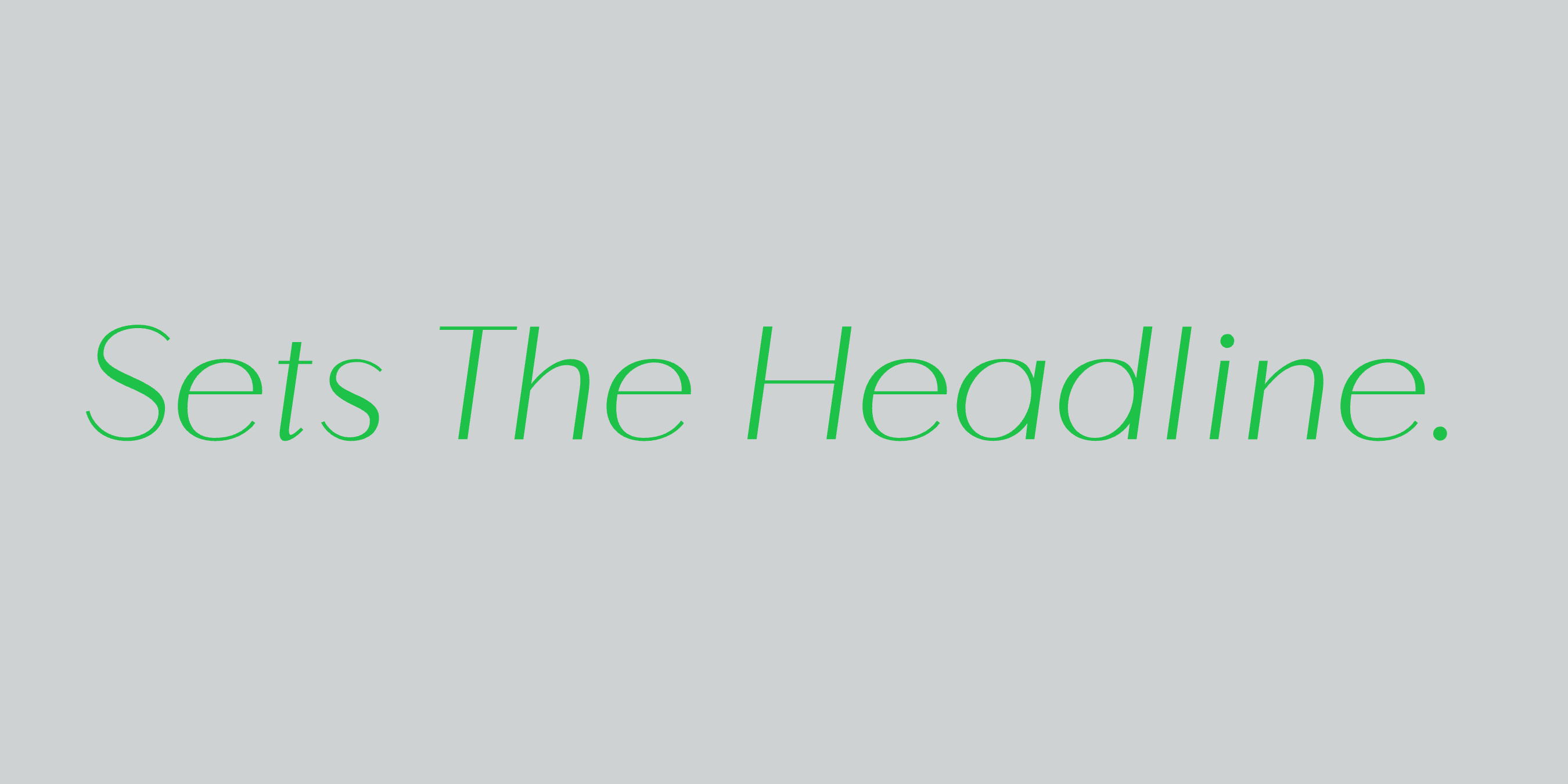
Moderne Display-Schriften für Editorial Design und Branding
Display-Schriften sind Typografie in ihrer ausdrucksstärksten Form. Wenn eine Überschrift selbst zum Bild wird und nicht nur ein Bild beschriftet, trägt die Schriftwahl die Marke. Diese zehn Mojomox-Schriften sind für genau diesen Fall gemacht. Manche sind ruhig und editorial, manche laut und architektonisch, manche warm und durchdacht. Alle funktionieren in großen Größen, in denen jede Kurve genau betrachtet wird.
Swav
Wellige, futuristische Display-Schrift mit fließenden Buchstabenformen. In großen Größen wirkt sie zukunftsgewandt und selbstbewusst. Gut für Mode, Musik und Magazincover.
Swav testen →Saltz
Schmale Serifenschrift mit scharfen Formen für redaktionelle Titel. Markante Proportionen in großen Größen, gut lesbar in kleineren. Eine bewährte Wahl für Mode- und Beauty-Magazine.
Saltz testen →Aezra
Schmale Serifenschrift mit scharfen Formen und langen Endstrichen. Die schmalen Proportionen und detailreichen Endungen geben Aezra in großen Größen viel Charakter.
Aezra testen →Ques
Breite, elegante Schrift im Stil einer Serifenschrift, mit Kontrast. Die breiten Proportionen und feinen Striche wirken in großen Größen selbstbewusst und editorial.
Ques testen →Roma
Moderne, elegante Groteskschrift mit Strichkontrast. Der Kontrast gibt ihr Gewicht in Überschriften, die humanistische Grundform hält sie warm. Gut für Editorial- und Modeprojekte.
Roma testen →Auria Sans
Moderne Groteskschrift mit weichen Innenecken. Sie macht als große Überschrift eine sehr gute Figur und wirkt dabei zeitgemäß statt dramatisch.
Auria Sans testen →Apex
Kräftige, spitze Groteskschrift mit scharfen Alternativbuchstaben. Eine verlässliche Display-Schrift für große Überschriften, Plakatwände und Verpackungen, die auffallen sollen.
Apex testen →Cesty
Freundliche, runde Display-Schrift mit 70er-Einfluss. Die warmen Proportionen und weichen Ecken wirken selbstbewusst, aber nicht aggressiv. Gut für Food, Gastronomie und Lifestyle.
Cesty testen →Bauhaus Geo
Geometrische Display-Schrift, auf das Wesentliche reduziert. In großen Größen wirkt sie ruhig und bestimmt. Die passende Wahl, wenn eine Marke Struktur statt Ausdruck sucht.
Geo testen →Mod
Moderne Serifenschrift mit eleganten Proportionen. Selbstbewusste Striche, ohne dramatisch zu sein. Für Überschriften, die edel wirken sollen, ohne sich in den Vordergrund zu drängen.
Mod testen →Display- oder Textschrift: die passende Schrift für den Zweck
Display-Schriften sind für große Größen gemacht (ab 24 pt). Ihre Proportionen, ihr Kontrast und ihre Details sollen betrachtet werden, nicht in langen Absätzen gelesen. Deshalb gehört zu ihnen eine Textschrift, die sich schnell liest. Der Mojomox-Katalog enthält serifenlose Schriften und Serifenschriften für Fließtext (Vole, Roma, Auria Sans, Mod), die sich gut mit jeder der Display-Schriften oben kombinieren lassen.